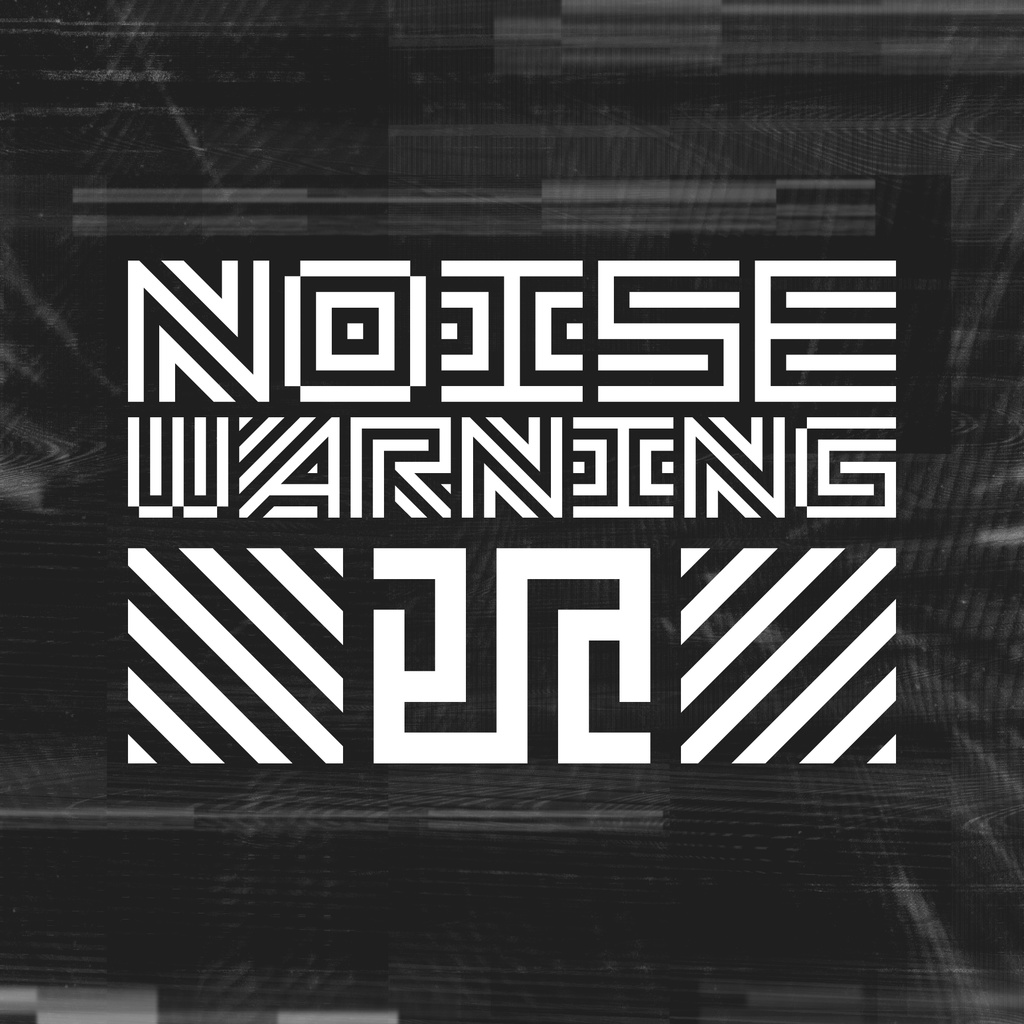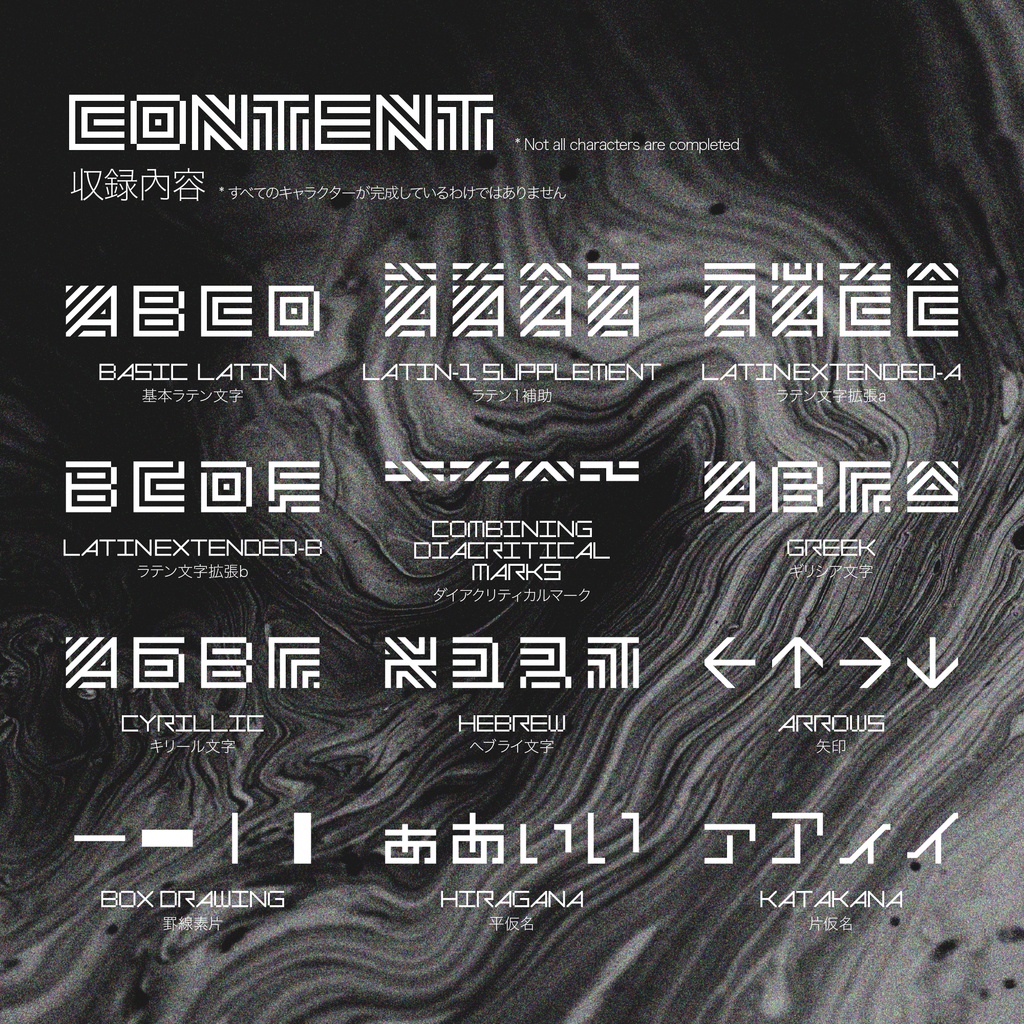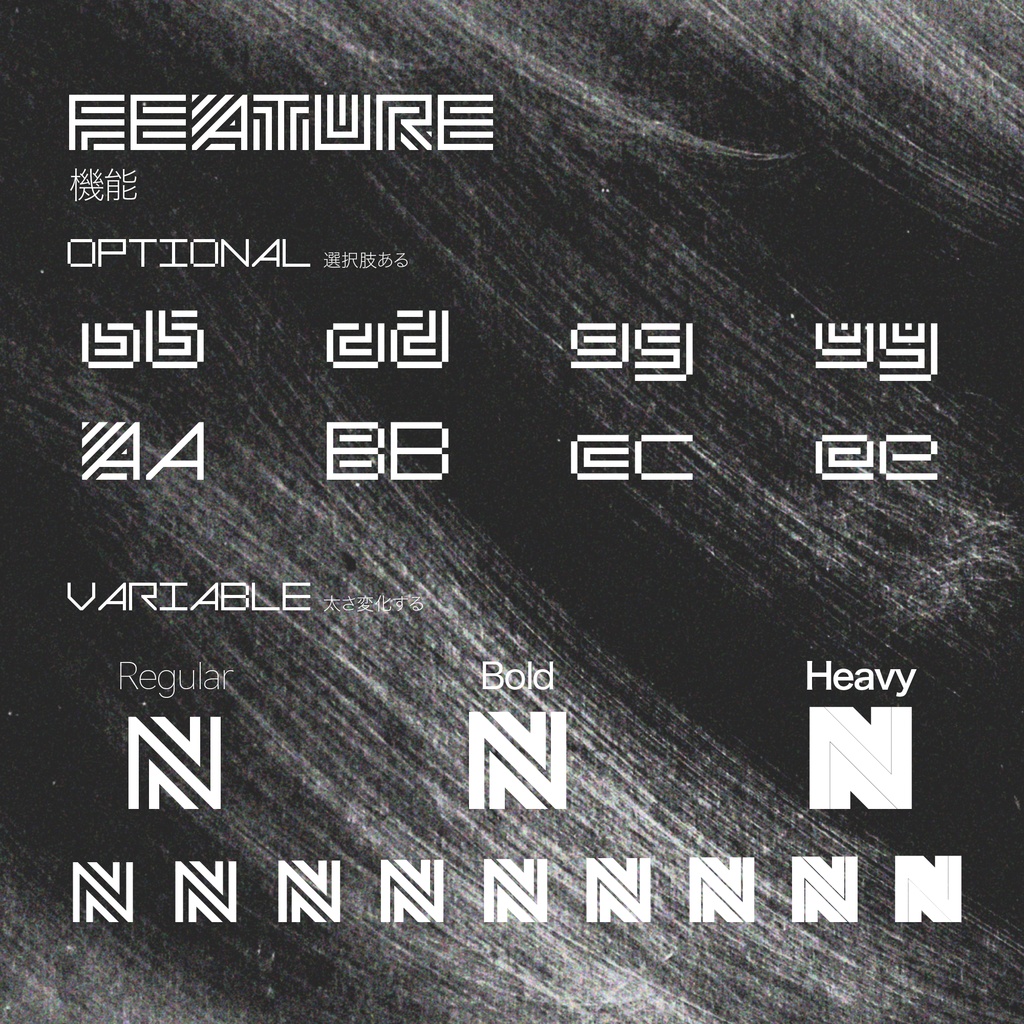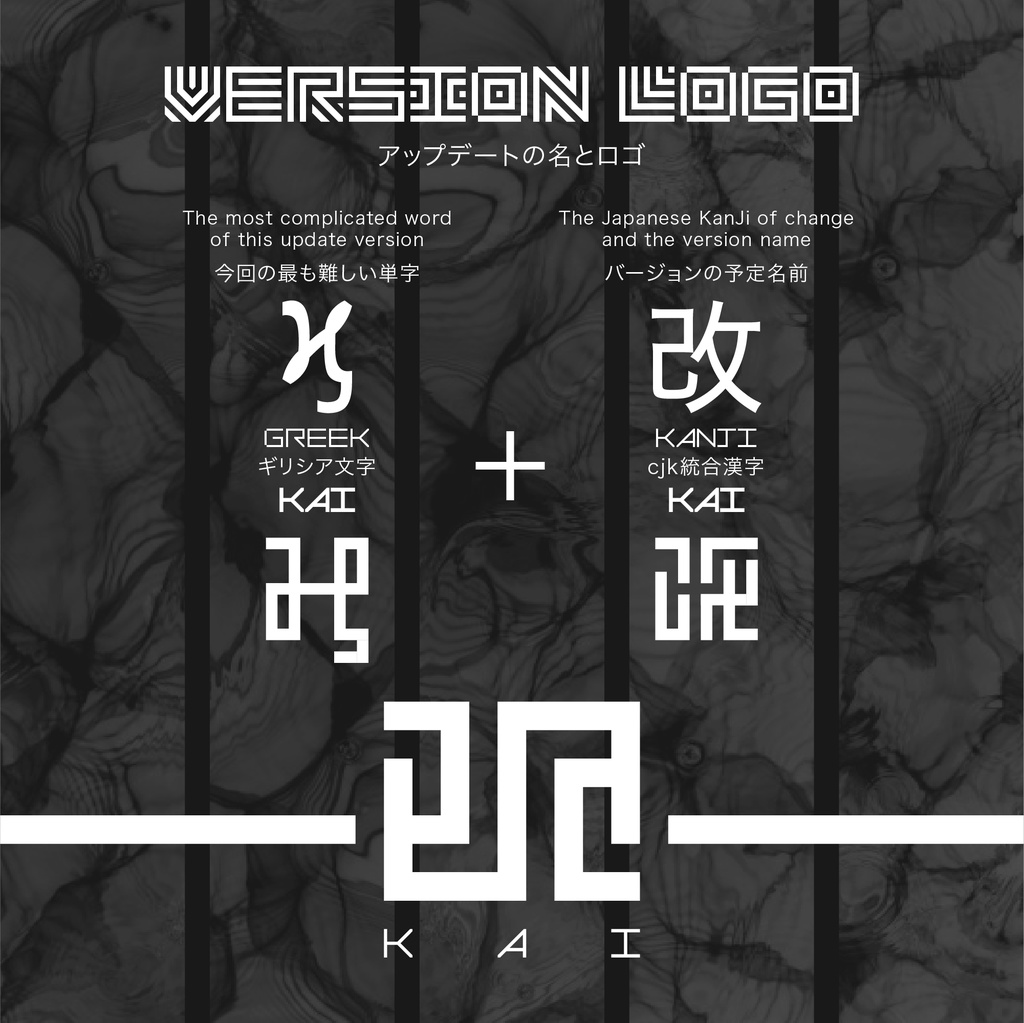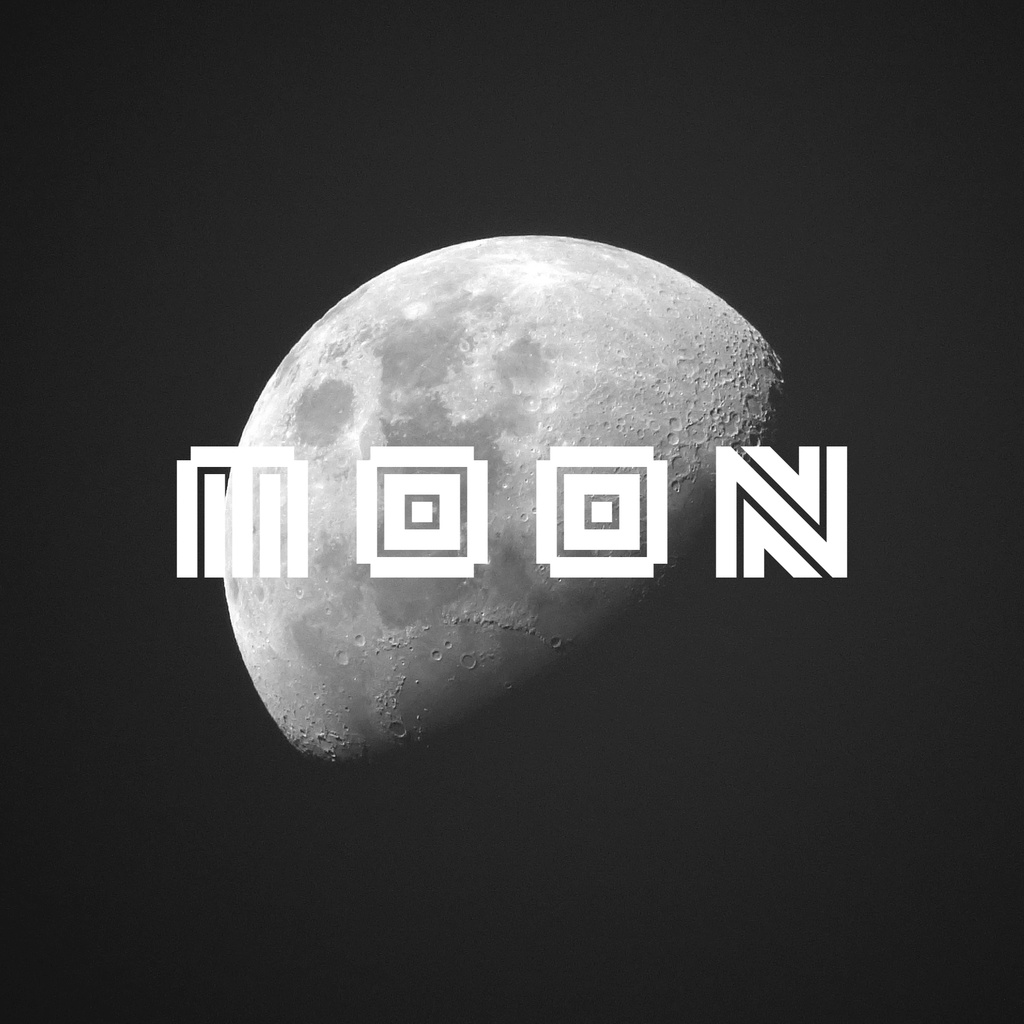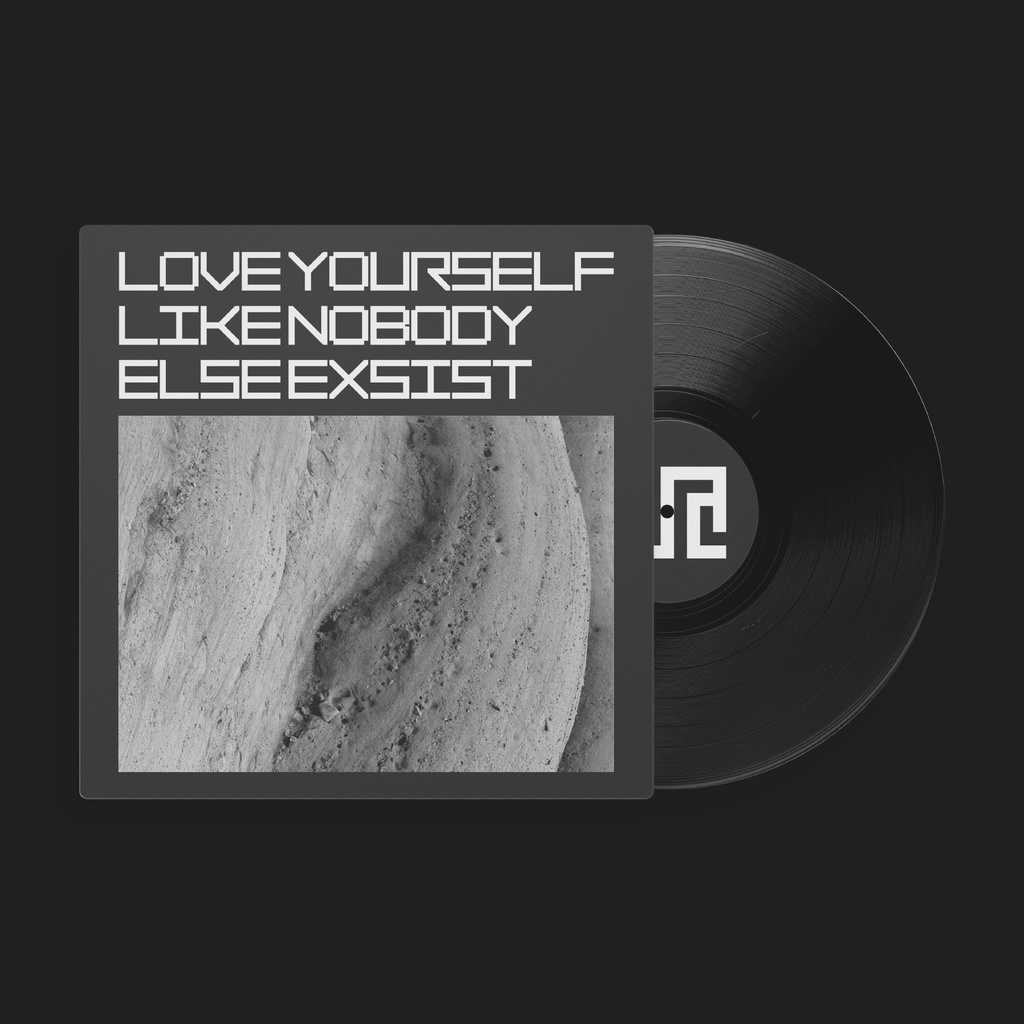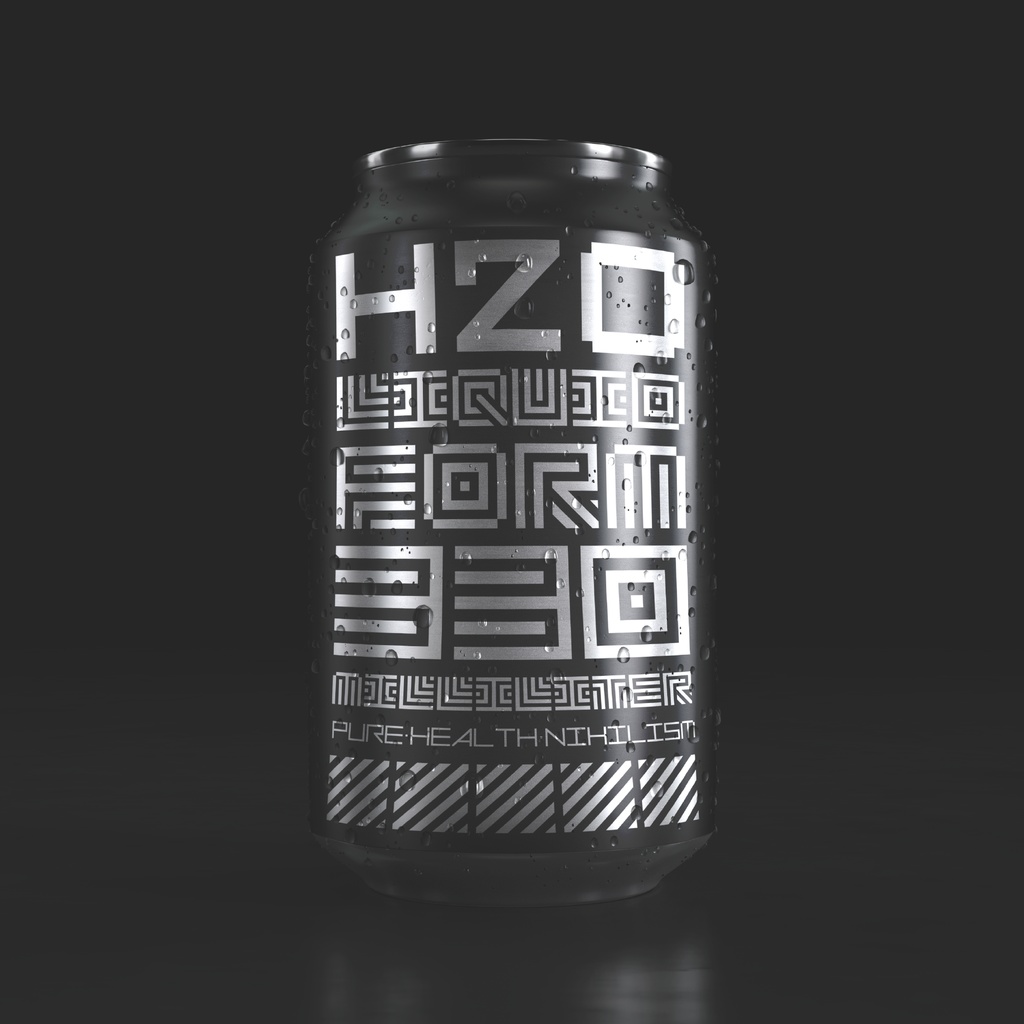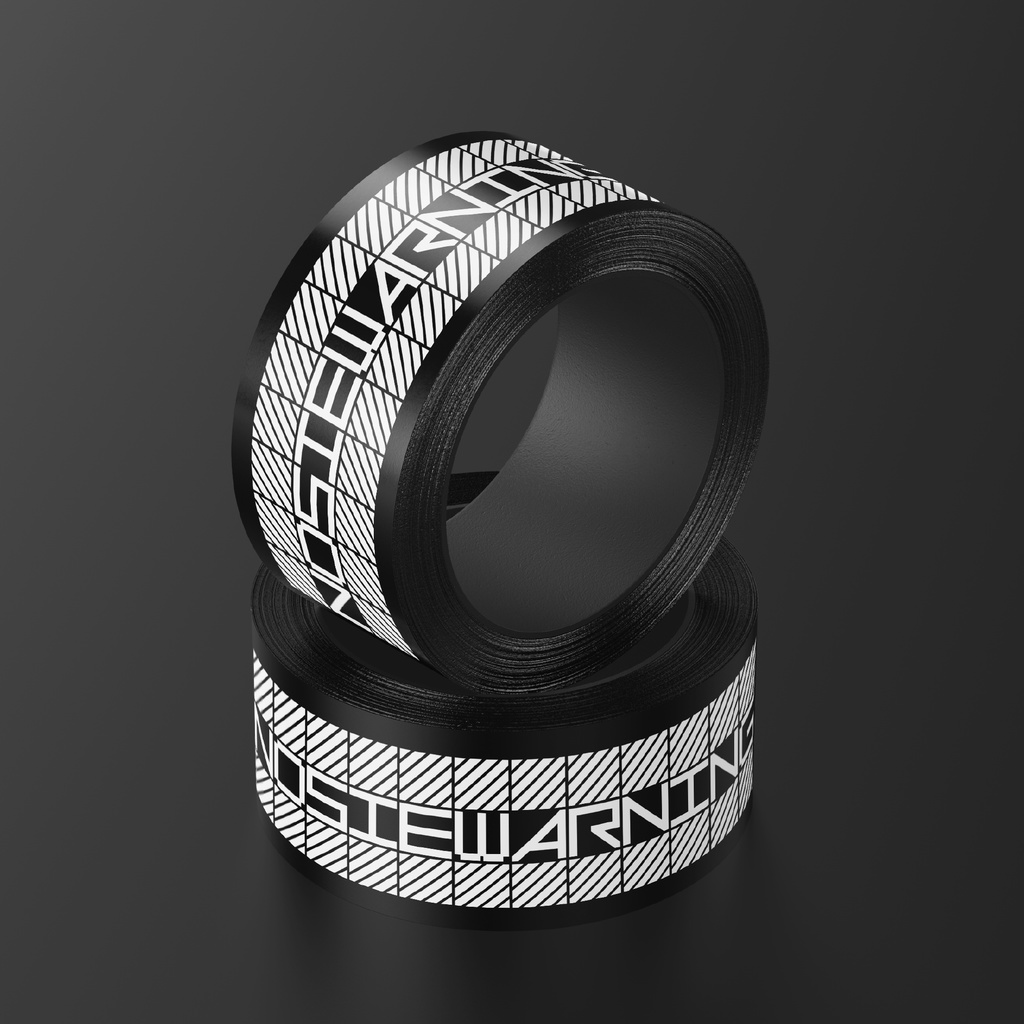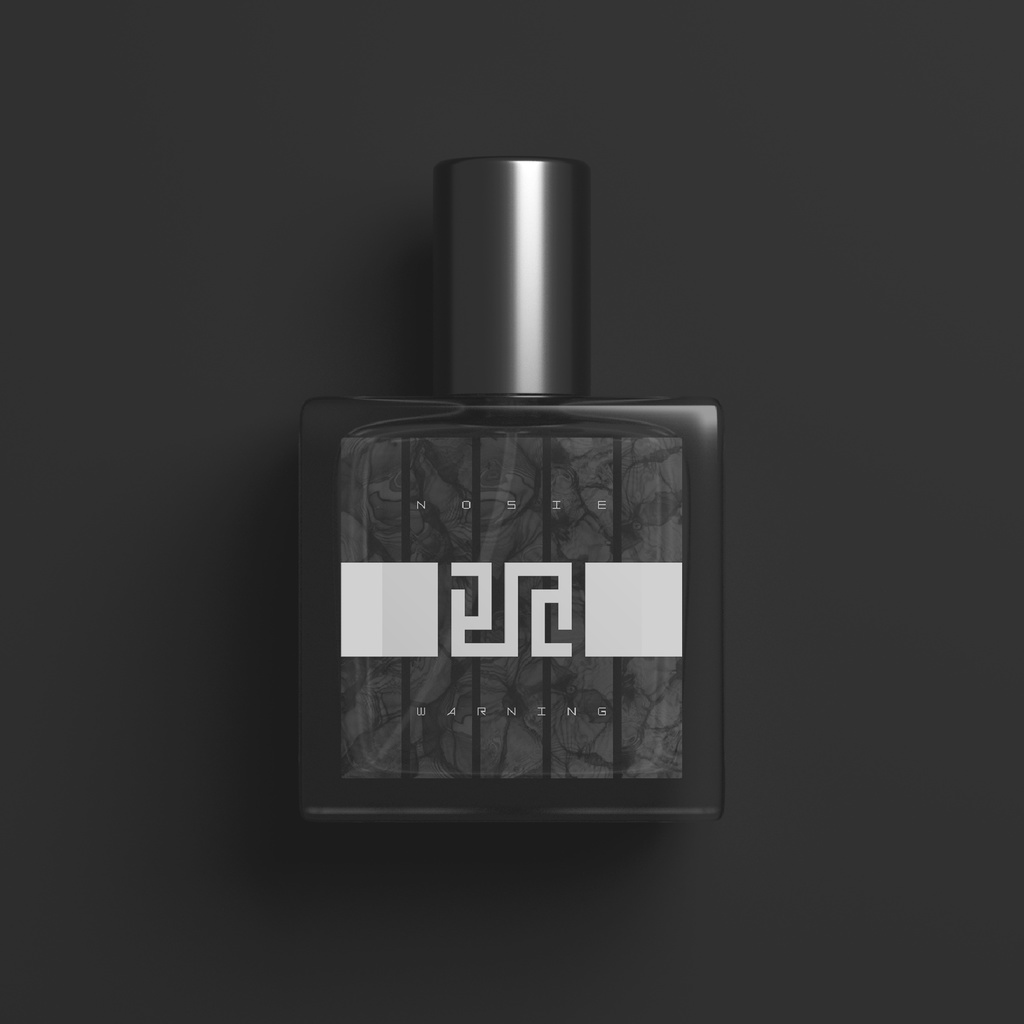
無料【フリー可変フォント】騒音警示·改 Nosie Warning-ϗ「一時的に無料」
騒音警示·改|Nosie Warning-ϗ「一時的に無料」 📢📢📢特記事項📢📢📢 フォントに含まれる文字のほとんどは、母国語ではないので、何か気を悪くされたのでしたら、お許しください。 📢デザイン説明 騒音警示はわれら作成する最初のフォントシリーズです。今年の「騒音」の作字を拡張した内容です。 視覚的な調和と超現実的な視覚効果を感じできる。 今回のアップデート「改『ϗ』」バージョンが、フォントの太さの幅を変更する機能と、2つの幅のプリセットが追加されました。 このアップデートの名とロゴは、一番複雑だと思うのギリシャ文字「ϗ」と漢字「改」を組み合わせで完成です。 どちらの文字も「カイ」と発音します。 📢利用規約 このフォントは無料でダウンロードできる。 個人、商用どちらでも利用可能です。 もしもこのフォントが使用されたら、https://twitter.com/amari_designに教えていただけるとうれしいです! 本素材を使用した作品については、リツイートなどの形で宣伝させていただく場合があります。 フォントのインストール等の技術的なサポートはいたしません。使用して発生したと思われる如何なる問題についても、作者は責任を負わないものとします。 著作権を放棄することはありません。 商標を登録したり、作者であると主張したり、データ自体を販売または再販したりすることは禁じられています。 このコンテンツの最終的な解釈権は作者に帰属します。 内容補充とバージョン更新は製作続けるです。使用する際は最新バージョンにご注意ください。 📢収録內容 騒音警示·改はラテン文字、ギリシア文字、キリール文字、ヘブライ文字、仮名といろいろを含む1574文字が含まれています(一部のフォントには複数の選択肢があります)。 ーーーーーーーーーーーー Twitter:https://twitter.com/amari_design Behance:https://www.behance.net/9f45706b ーーーーーーーーーーーー